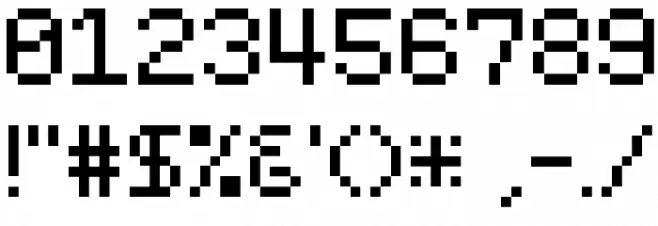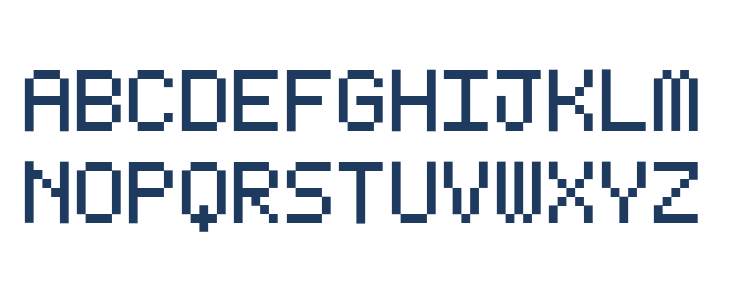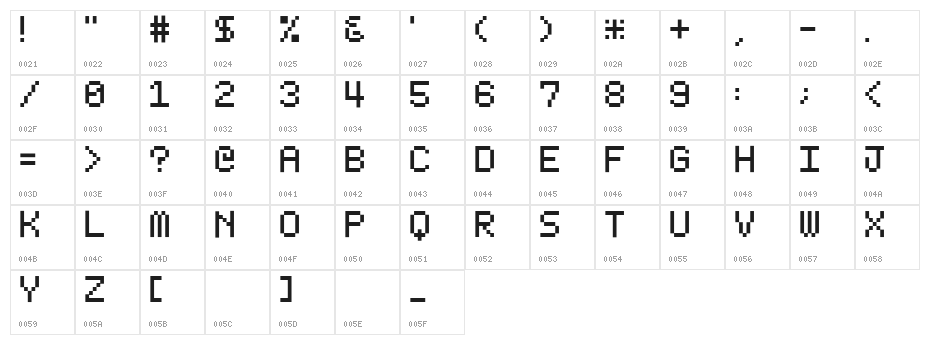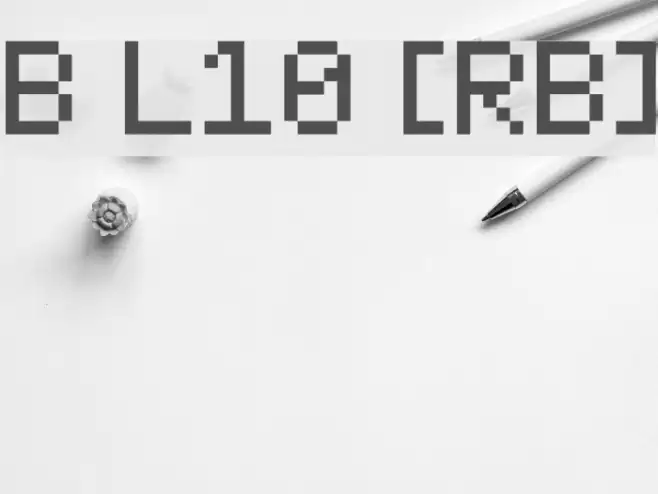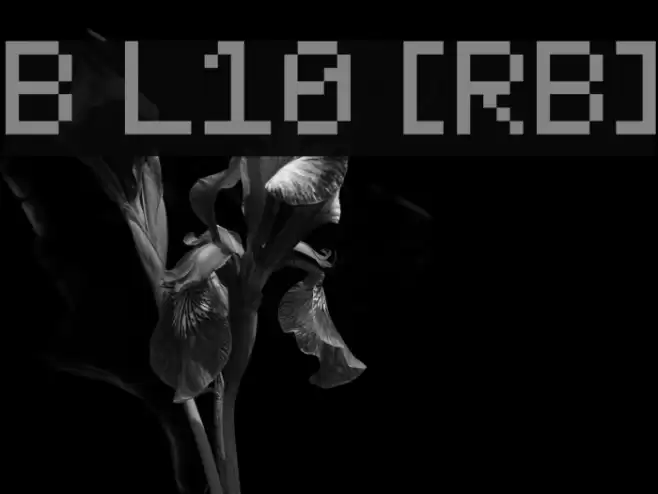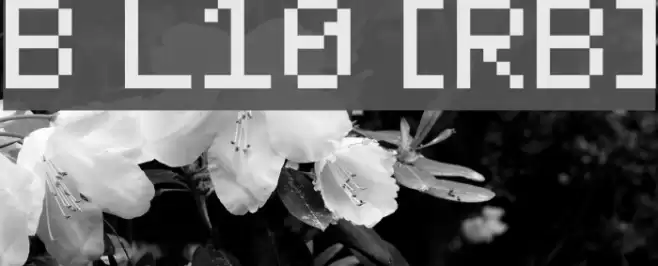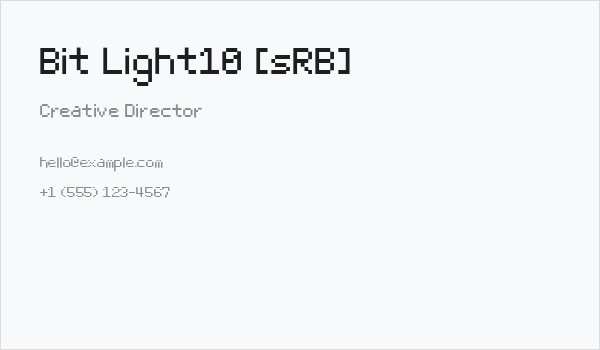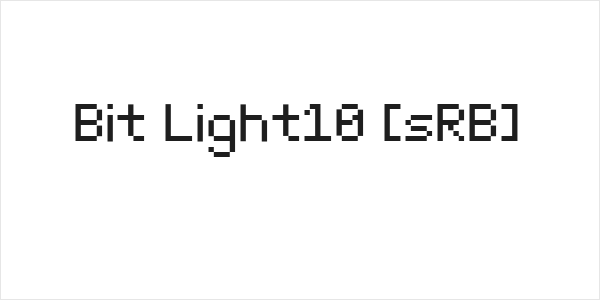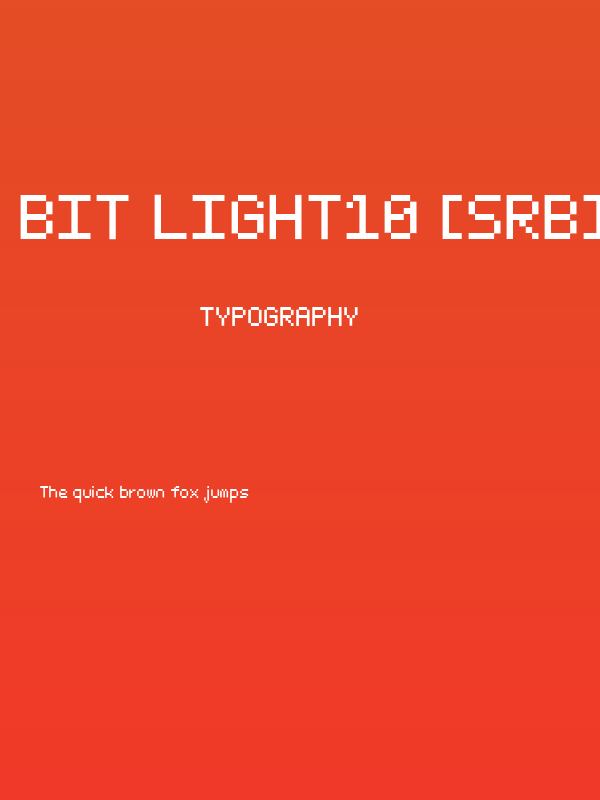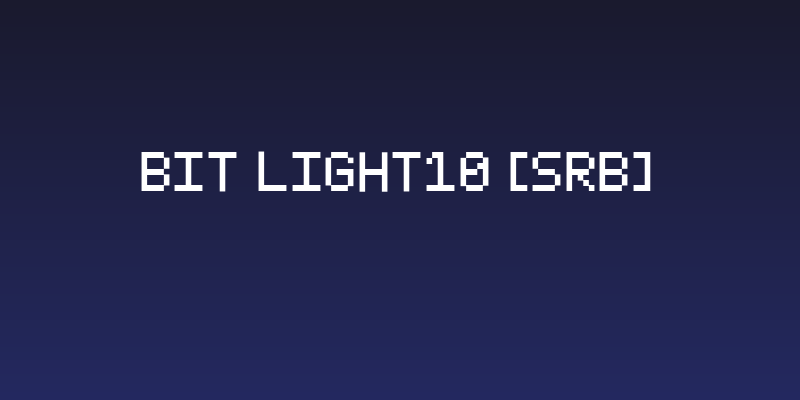
Bit Light10 [sRB] Font
| Категория | Pixel |
| Общий стиль | Vintage |
| Область применения | Logos, Headlines, Digital displays |
| Рекомендуемые проекты | Ideal for retro video game designs, digital art projects, tech-themed posters, and any creative work that requires a vintage digital aesthetic. |